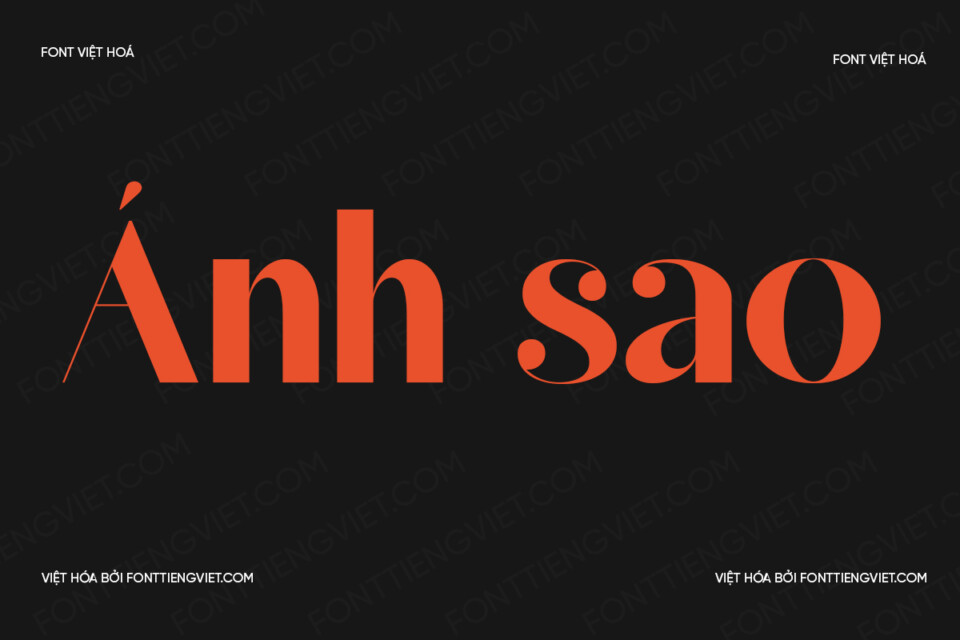
Tên font: Font Việt hóa VIP Mirage
Tác giả: VampStudio
VIP Mirage Việt hóa là một font chữ không chân (sans-serif) độc đáo, được thiết kế theo phong cách của font có chân (serif). Font này mang đến vẻ ngoài tinh tế, hiện đại nhưng vẫn giữ được sự sang trọng và cuốn hút của các font cổ điển. Nét chữ gọn gàng của font không chân kết hợp với sự duyên dáng của font có chân đã tạo nên một tổng thể hài hòa và đầy cá tính, lý tưởng để tạo điểm nhấn độc đáo và thu hút mọi ánh nhìn trong các thiết kế đòi hỏi sự thanh lịch và phong cách riêng.
Với đặc điểm thiết kế độc đáo, đường nét sắc sảo và khả năng gợi cảm xúc mạnh mẽ về sự sang trọng, VIP Mirage là lựa chọn hoàn hảo cho các ấn phẩm trong lĩnh vực thời trang và ẩm thực: